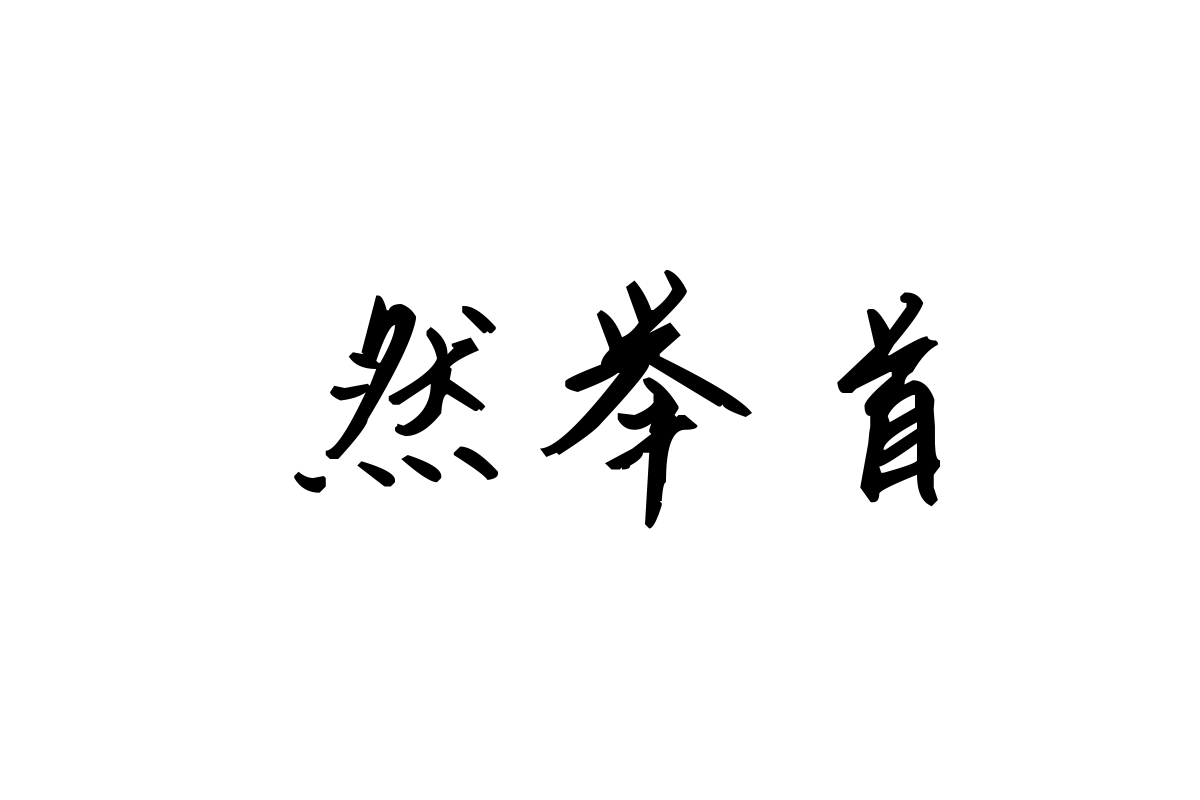
米开咖啡别加糖字体是一套由设计师为品牌“米开咖啡”特别设计并发布的字体。这套字体具有现代、时尚的设计风格,适用于各种商业和品牌推广场合。
字体特点:
1. 简洁易读:米开咖啡别加糖字体采用简洁的字形设计,使得文字易于阅读和识别,适合在各种媒介上使用。
2. 时尚感:字体线条流畅,具有一定的时尚感,能够吸引年轻消费者的注意力。
3. 可定制性:该字体支持多种字号和样式选择,满足不同场景的需求。此外,还提供了一些特殊字符和符号,使字体更加丰富多样。
总之,米开咖啡别加糖字体是一款非常适合用于品牌推广和广告设计的优秀字体。